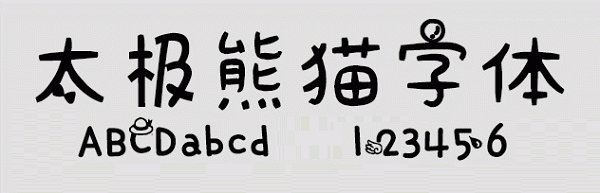
太極熊貓?bào)w免費(fèi)版
太極熊貓體字體是一款像熊貓一樣可愛(ài)的中文字體,字體中融入了超多熊貓的的卡通頭像,看起來(lái)非常的豐富,字體整體比較的圓潤(rùn),排版之后整體效果更好哦,喜歡的用戶快來(lái)綠色資源網(wǎng)下載吧!
太極熊貓?bào)w簡(jiǎn)介:
太極熊貓?bào)w字體是一款可帶的中文簡(jiǎn)體字體,用于熊貓?jiān)O(shè)計(jì)方面,整體字體筆畫(huà)均衡,識(shí)別性強(qiáng),在字體見(jiàn)嵌入啦許多卡通圖案,使字體與圖案相結(jié)合具有創(chuàng)意性,本作品適用于創(chuàng)意設(shè)計(jì)字體、藝術(shù)設(shè)計(jì)字體!
太極熊貓?bào)w字體特色:
最大特色就是將漢字與圖形相互融合為一體,并且不會(huì)影響漢字辨識(shí)度,
包含了熊貓頭、蝴蝶結(jié)、小恐龍、小翅膀等各種卡通圖案,
支持簡(jiǎn)體漢字、拼音字母、數(shù)字符號(hào)等,
適合應(yīng)用到平面設(shè)計(jì)、廣告制作等字體中使用!